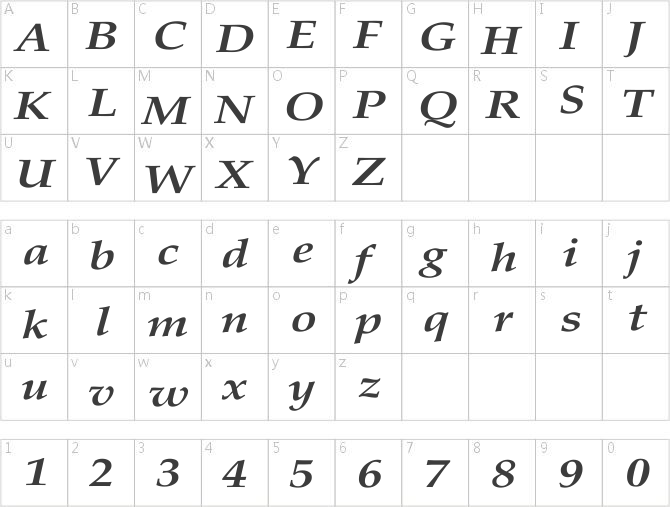
字體名稱: Palatin
Palatino-BoldItalic-Wd
Palatino-BoldItalic-Wd介紹
Palatino-BoldItalic-Wd字體字庫是一款讓人賞心悅目、百看不厭的英文字體,適合各類廣告和產品包裝設計應用,字體大小0.13MB,格式為ttf字體,上傳用戶是多喝燙水,作者/版權方為未知